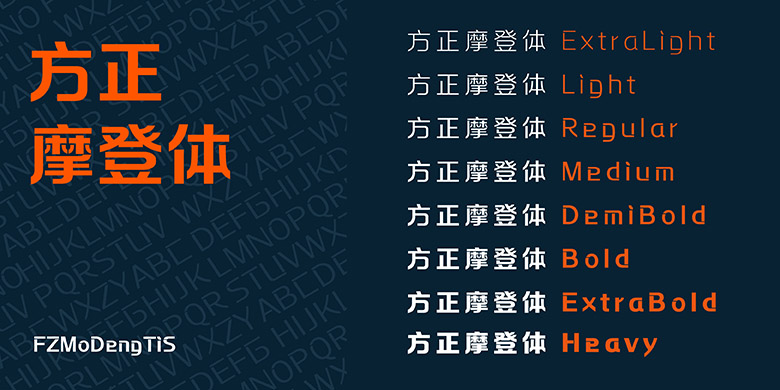
方正摩登体-简繁-ExtraLight系列字体
摩登体设计灵感源于观看一场国际单车比赛,一台赛车后面有特式标志(LOG 因此有感而来,由于这高级科技的赛车,充满时代感,所以命名为“摩登体 摩登体设计配合前卫潮流的感觉,左面用直线,右面用圆形表达,打破传统规所有“口”型有小缺口,增强不受束缚的时尚感受。它含8种不同粗细字体!摩登体适合年青人服装品牌, 体育运动器材,汽车,单车,啤酒,矿泉水等商业宣传和包装设